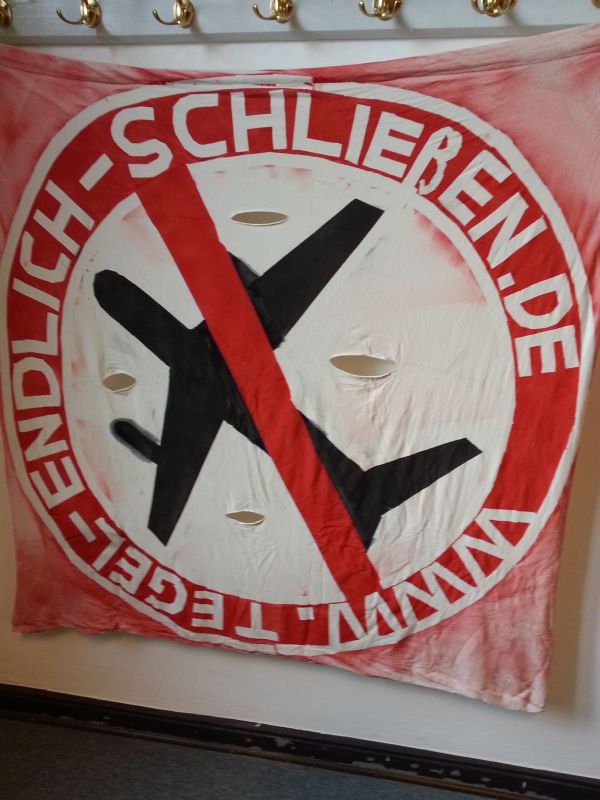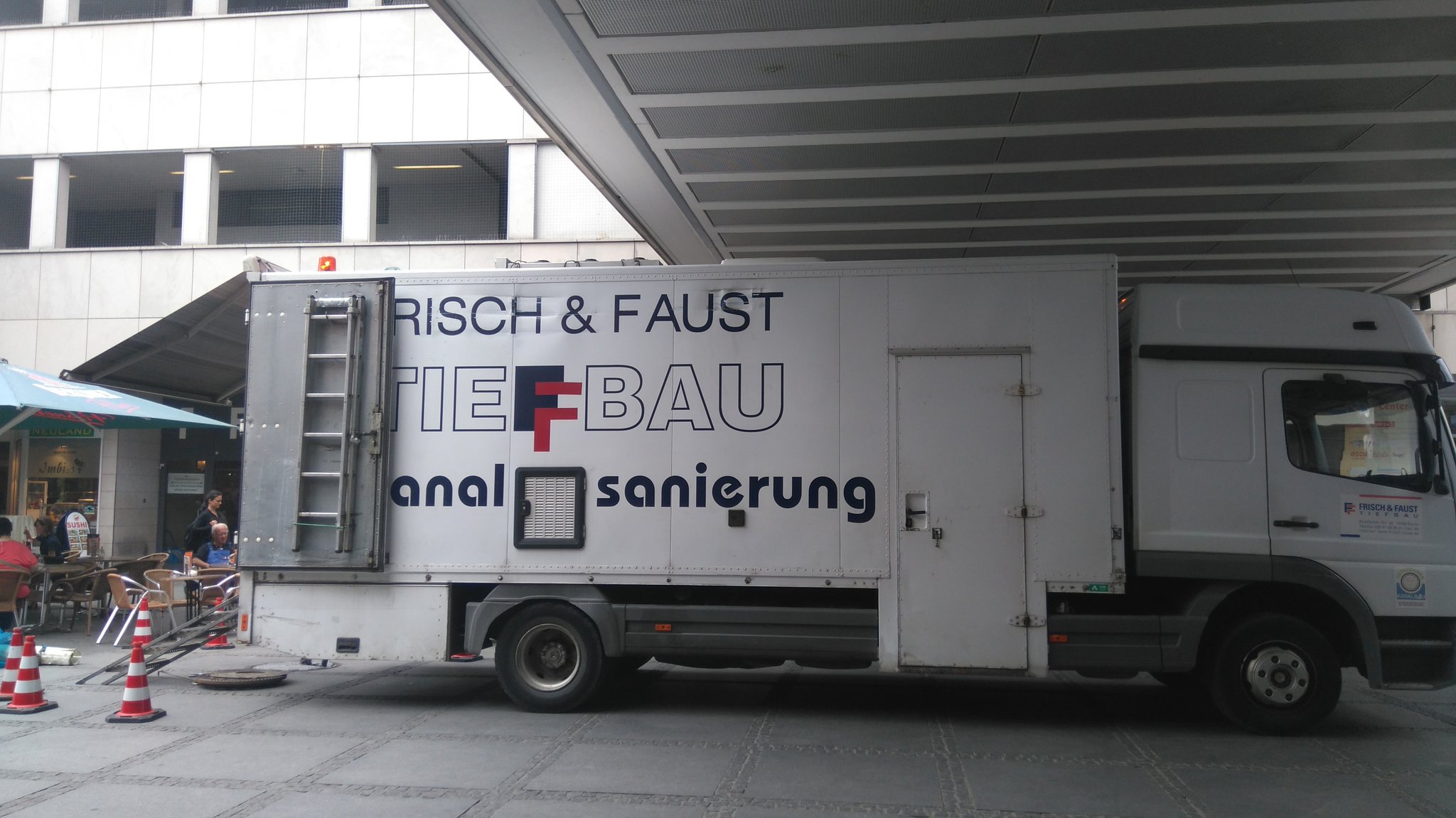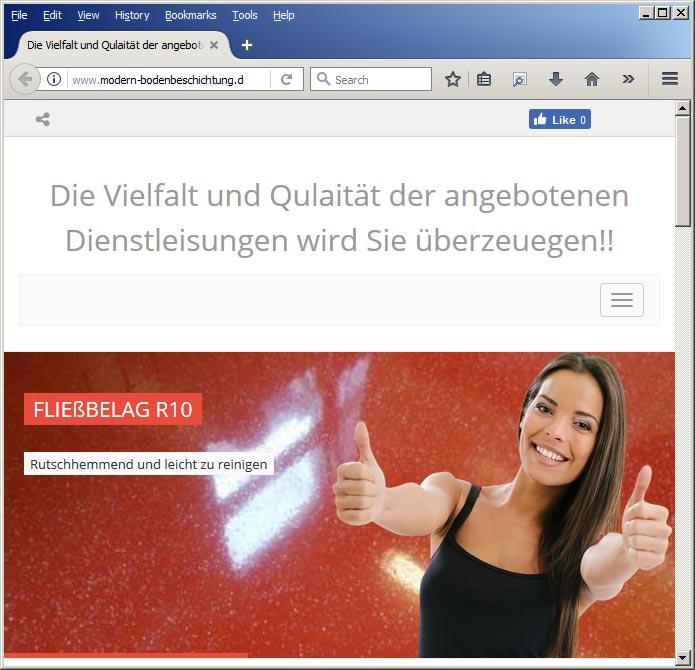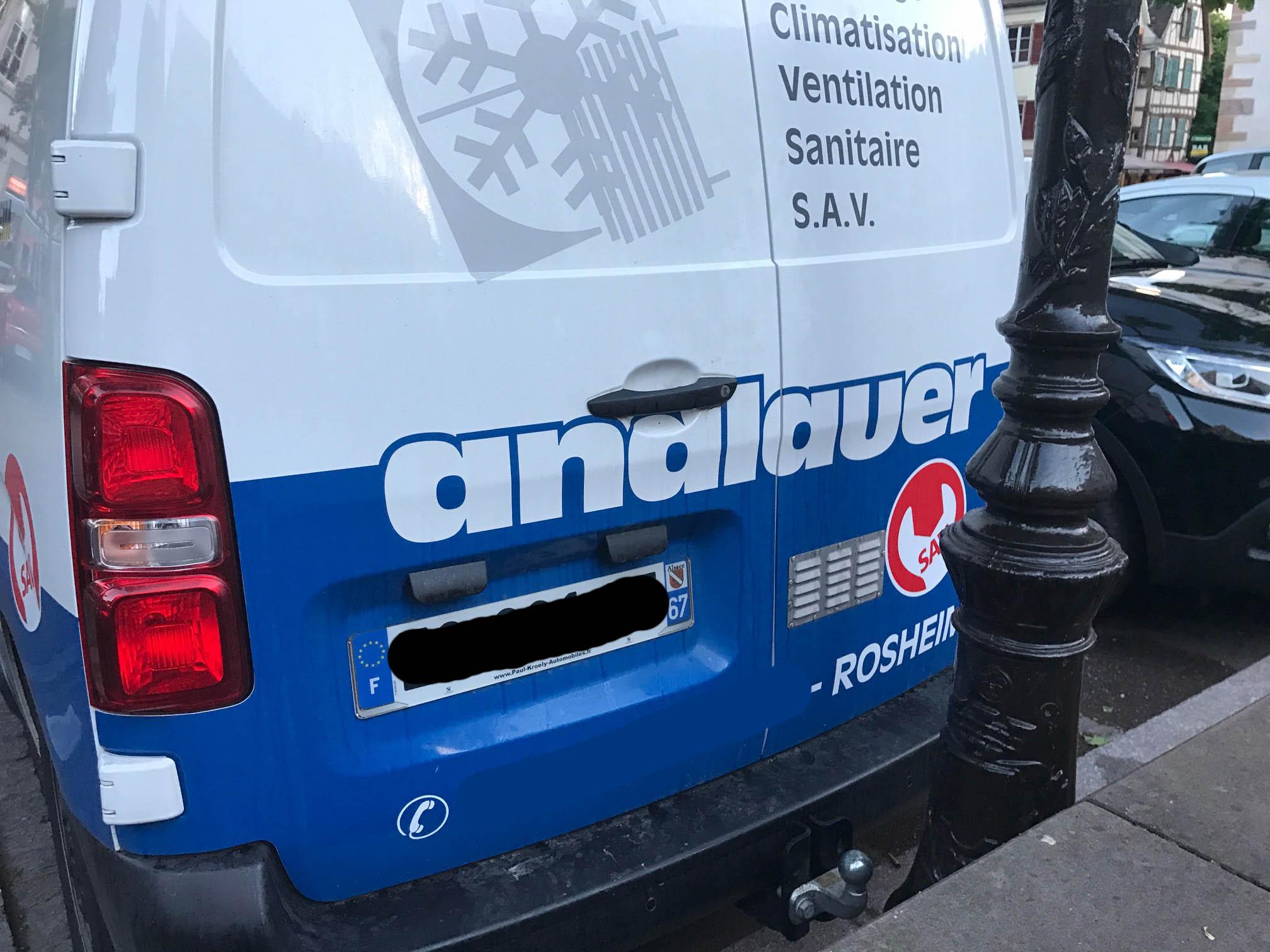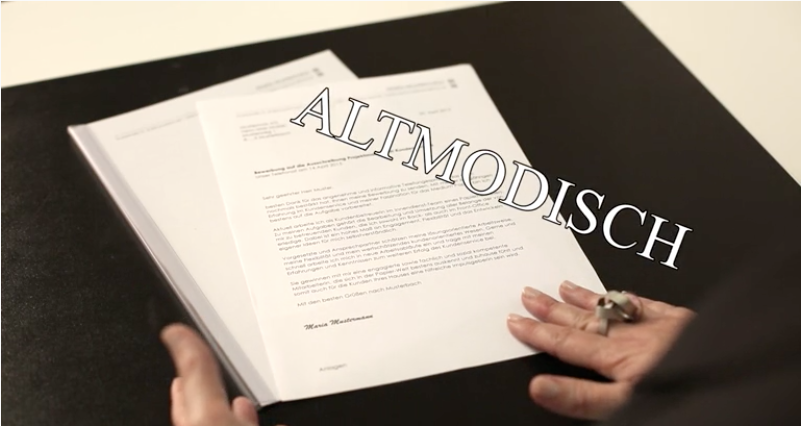
Muss man da eventuell rechts ums Fahrzeug herumlaufen, um den Rest der Beschriftung zu verstehen? Oder gehört das alles irgendwie zusammen???
Das ist ein vollständig wiedergegebenes Gesamtkunstwerk.
„Die Vielfalt und Qualität der angebotenen Dienstleistungen wird Sie überzeugen!“
So inhomogen, wie die aussehen, vermute ich, da hat der Setzer ein paar fetten Punkten mit der Ahle zu einer Pupille verholfen.
Helvetica, Calibri, ...
... und Centrury Gothic – und Unterschriften nach Möglichkeit mit Brush Script :mrgreen:
Das ist ja mal eine Text-Film-Schere
Eher ein Designfundstück zum Thema fragwürdige Logos:
Was willst du, ist doch wohl das passendste Logo überhaupt für diese Veranstaltung: Man kommt zusammen, tanzt ein wenig umeinander herum, und trennt sich dann, eine Verbindung geknüpft zu haben, aus der man sich, wie dies beim Diebesknoten nun mal so ist, rasch wieder zurückziehen kann, wie wir es ja gerade mit Donald's Rückzieher in Umweltfragen gesehen haben.
wie wir es ja gerade mit Donald's Rückzieher in Umweltfragen gesehen haben.
Moment. Die Gruppe der zwanzig wichtigsten Industrie- und Schwellenländer hat sich informell zusammengeschlossen. Die ist zwar in Bezug auf Klimagipfel von Bedeutung, hat aber nicht direkt etwas mit den UN-Klimakonferenzen zu tun, oder? Ich würde gar nicht wollen, dass die G20 sich so fest zusammenschließen, dass sie nur noch durch Zerschlagung trennbar wären. Also der Kreuzknoten war an sich keine schlechte Idee. Nur der Diebesknoten. Aber auch darüber könnte man streiten, denn die Dauer der G20-Gipfel ist ja festgelegt und ein Diebesknoten löst sich mit einer Geschwindigkeit, die abhängig von der Länge der losen Enden ist. Allerdings entfernen sich die festen Enden der Seile voneinander, während sich der Knoten löst. Und das widerspricht eigentlich dem Sinn solcher Konferenzen.
das war ja auch nur ein Beispiel, wie schnell ein geknüpfter knoten = Abkommen wieder auseinander gezogen werden kann. Das diese Veranstaltung von etwas anderer Art ist, weiß ich, nur hab ich es eben aufgegeben, davon wirklich bewegendes zu erwarten.
Ihr werdet es nicht glauben selbst Peters TGL 0-16 hat es in der Vergangenheit in ein Comic geschafft.
Wie ich darauf komme? in einem Interview mit den Zeichnern wurde erwähnt dass sie die Texte mit  Schablonen schreiben mussten. Das wurde aber dann irgend wann geändert. Denn das ist Manuell sicher mühseelig
Nun ja, als ich damals in der Lehre ein Berichtsheft führen musste, und das war damals noch keine Tabellarische Aufstellung über die am Tag geleisteten Arbeiten, sondern es sollte ein A4-Text in "Normschrift" sein, indem irgend eine erlernte Arbeit genau beschrieben werden sollte, ergänzt durch eine technische Zeichnung auf der Rückseite des Blatts. Also krakelte man so gut wie möglich die DIN16. Hach, was hätte ich drum gegeben, meinen Font zu haben :-)